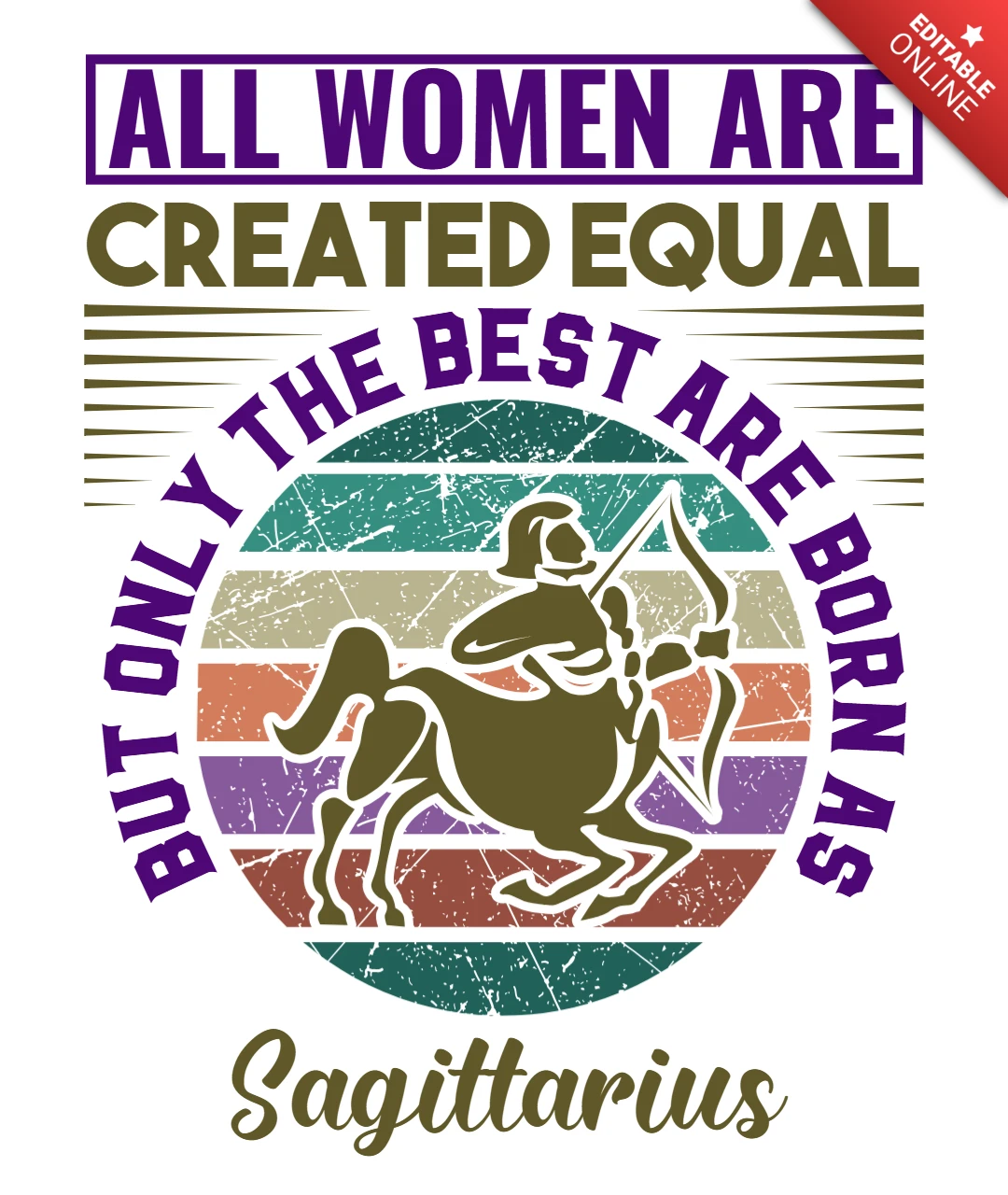
Bewerkbare retro typografie ontwerpsjabloon voor vrouwen van de Boogschutter
Bewerken in Design Studio Downloaden in JPGVersterk de positie van vrouwelijke Boogschutter met onze bewerkbare retro ontwerpsjabloon, met motiverende typografie en astrologische illustraties - perfect voor vieringen, merchandising of een attent cadeau!